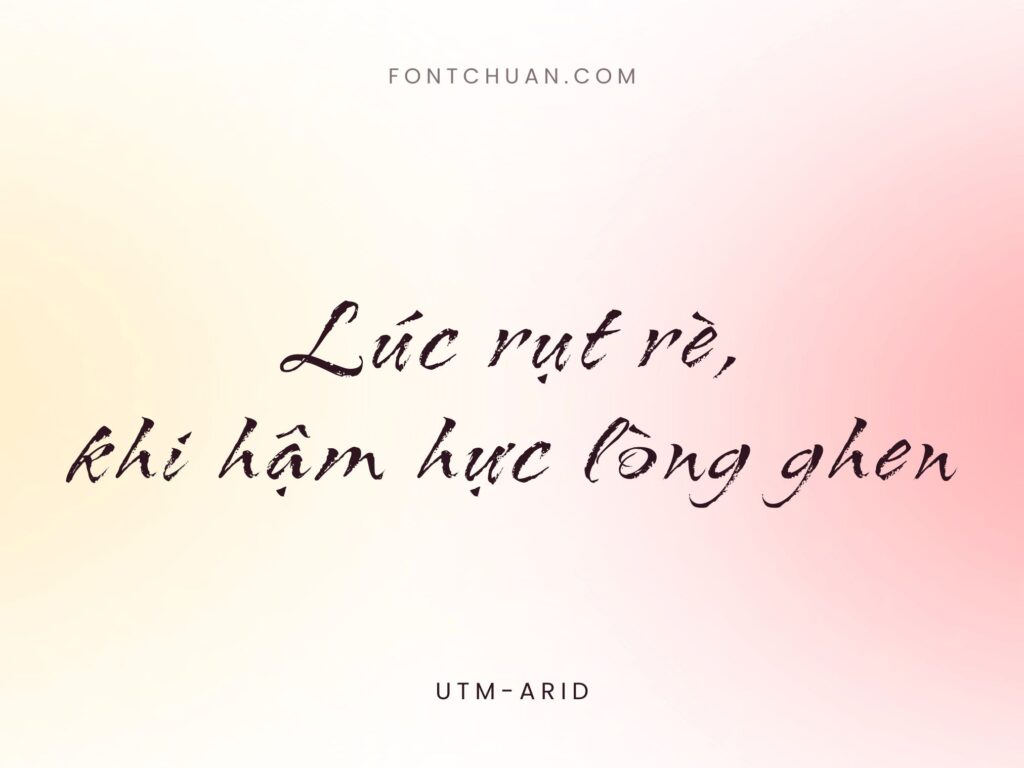
Font UTM Arid Việt Hóa
UTM Arid là một Font Script mang phong cách viết tay mềm mại và đầy cảm xúc. Các đường nét được vẽ như bằng bút lông, mang đến cảm giác nhẹ nhàng và thân thiện. Phiên bản Việt hóa do Đinh Kiên thực hiện giúp font hỗ trợ đầy đủ tiếng Việt cùng hơn 100 ngôn ngữ khác. Đây là một trong những font được thành viên Font Chuẩn sưu tầm và chọn lọc nhằm phục vụ cộng đồng thiết kế trong các dự án cá nhân hóa hoặc cần yếu tố nghệ thuật cao.
UTM Arid sở hữu các nét chữ uyển chuyển, liền mạch và độ dày ổn định, mang đậm đặc trưng của Font Handwritten, giúp font thể hiện tốt trong các thiết kế mang tính biểu cảm. Font rất phù hợp cho ứng dụng trong thiệp mời, logo, tiêu đề, nhãn hiệu mỹ phẩm hoặc bao bì sản phẩm thủ công. Những ngành nghề như quảng cáo, thiệp cưới, giáo dục và ẩm thực hoàn toàn có thể sử dụng UTM Arid để tạo điểm nhấn duyên dáng và tinh tế trong thiết kế.